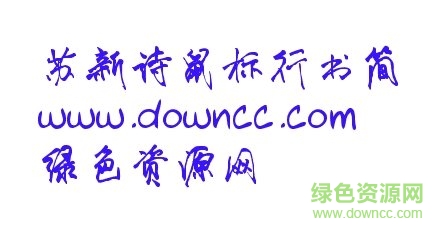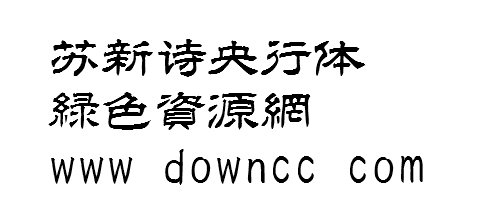
蘇新詩(shī)字體打包收錄了蘇新詩(shī)現(xiàn)已推出的十款字體,有三款字體正在制作中,本系列字體大氣嚴(yán)謹(jǐn),兼具藝術(shù)字體、手寫字體、行書(shū)字體等多種特色,為了方便用戶更好的體驗(yàn),綠色資源網(wǎng)帶來(lái)了最全的蘇新詩(shī)字體合體,免費(fèi)下載體驗(yàn)吧!
蘇新詩(shī)柳楷
蘇新詩(shī)藝標(biāo)簡(jiǎn)
蘇新詩(shī)爨寶子碑簡(jiǎn)
蘇新詩(shī)古印宋簡(jiǎn)
蘇新詩(shī)毛糙體
蘇新詩(shī)雙勾體
蘇新詩(shī)卵石體
蘇新詩(shī)鼠標(biāo)行書(shū)簡(jiǎn)
蘇新詩(shī)央行體
蘇新詩(shī)指畫體
蘇新詩(shī)魏碑簡(jiǎn)
蘇新詩(shī)大顏楷
蘇新詩(shī)仿魏繁
(后三款字體正在創(chuàng)作中)
蘇新詩(shī)河南商丘人,自幼受父親熏陶,酷愛(ài)書(shū)法美術(shù),特別對(duì)筆畫瘦硬、骨氣凜然的柳體楷書(shū)更是情有獨(dú)鐘,多年筆耕不輟,臨習(xí)名家碑帖,真、草、隸篆諸體都有涉獵。
蘇新詩(shī)所研發(fā)的“蘇新詩(shī)柳楷體”已與方正公司合作,成為一款可以用于商業(yè)設(shè)計(jì)的書(shū)法字體,被稱為中國(guó)首位。